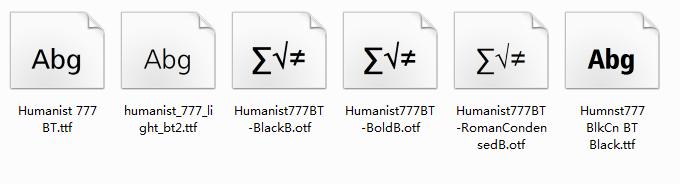
humanist777bt-blackb系列
humanist777bt系列字體合集收錄了humanist777bt-blackcondensedb、humanist777bt romanb、humanist777bt boldb共六款無襯線字體,從細(xì)到粗全部囊括,有需要者歡迎免費(fèi)下載!
字體性格介紹
1.粗筆畫字體在排版上會(huì)形成高密度的文本塊,這是因?yàn)楣P畫加粗,字體的負(fù)空間就會(huì)減小,視覺面積加重,產(chǎn)生一種壓迫感,進(jìn)而形成視覺重心,產(chǎn)生強(qiáng)調(diào)的作用。所以粗體字經(jīng)常用于標(biāo)題和標(biāo)語上,占據(jù)顯眼的位置,產(chǎn)生強(qiáng)調(diào)的作用。
2.細(xì)筆畫字體在視覺面積上較淡較輕,縮小了視覺面積后,筆畫負(fù)空間增大,結(jié)構(gòu)顯得疏朗清透,較小的視覺分量亦不會(huì)讓讀者產(chǎn)生壓迫感。
humanist777bt-blackb系列